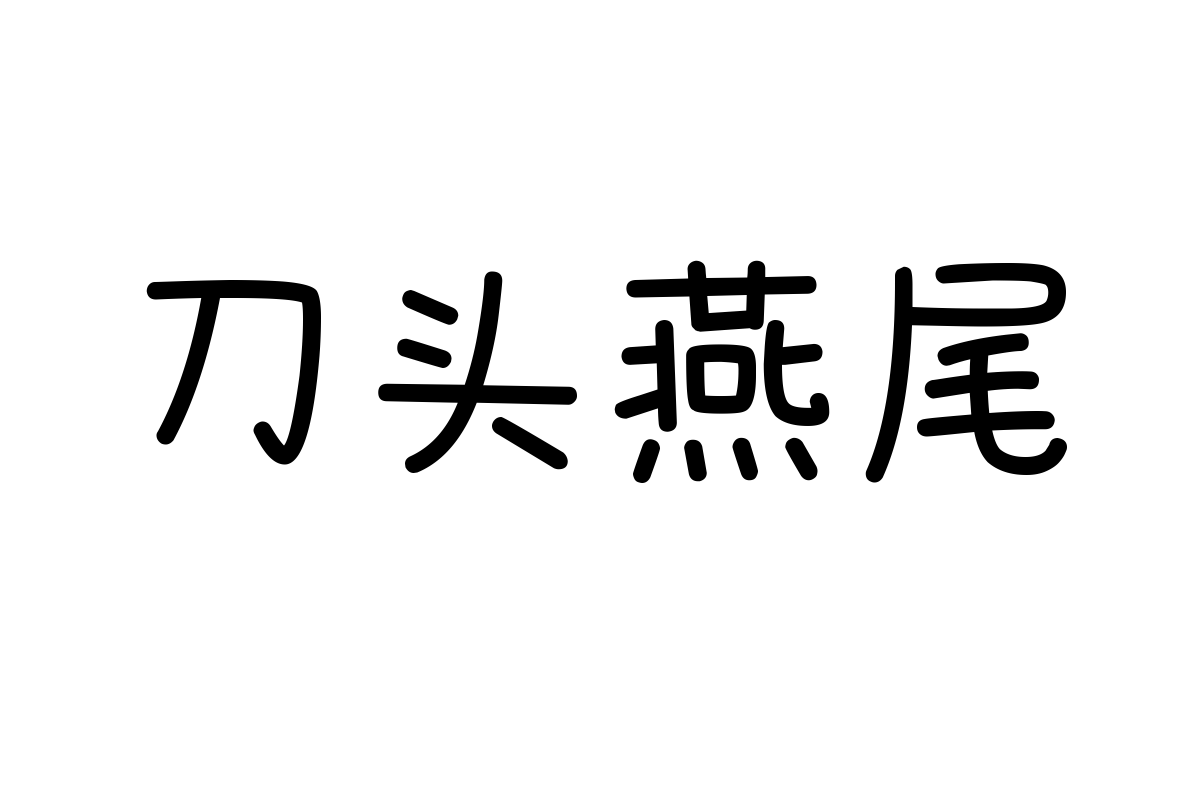
也字工厂快乐星球体是一种具有独特风格的字体,它结合了现代感和趣味性,给人一种轻松愉快的感觉。这种字体的特点是字形圆润饱满,线条流畅自然,给人一种亲切、友好的感觉。同时,也字工厂快乐星球体还具有一定的艺术性,字形的排列组合呈现出一种独特的美感,让人在阅读时能够感受到愉悦和轻松的氛围。
总的来说,也字工厂快乐星球体是一种适合用于儿童读物、广告宣传等场合的字体,它的可爱风格和亲和力能够吸引人们的注意力,让人们在阅读中获得愉悦的体验。